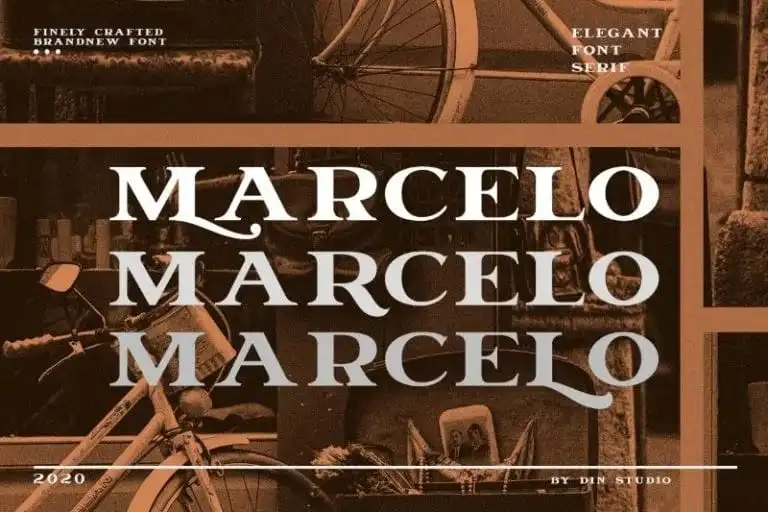
Marcelo Serif Font – Download Grátis
A ‘Marcelo Serif Font’ é uma tipografia serifizada que traz a modernidade num estilo contemporâneo. Com seu feixe de letras semi-condensadas e linhas serpentinamente afiadas, ela destaca-se como um tipo para fontes exibidas, perfeito para branding e criação de logotipos. Esta tipografia foi criada pelo Din Studio e é adequada para uma variedade de projetos, desde template para impressão até identificação visual completa. Com a ‘Marcelo Serif Font’, seus designs se tornam ainda mais bonitos e inspiradores. É um recurso valioso para qualquer projeto que precise de uma fonte serifizada profissional.